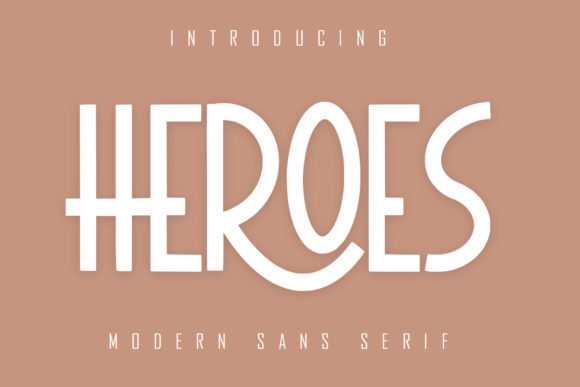
Heroes Font
Heroes Font adalah sebuah jenis huruf modern yang dirancang khusus untuk proyek-proyek bertema kepahlawanan, petualangan, dan keberanian—mulai dari poster film superhero hingga identitas merek game aksi. Dengan siluet tebal, kontras tinggi, dan sentuhan dekoratif yang terinspirasi oleh tipografi komik klasik serta desain logam tempa, font ini berhasil menyampaikan kekuatan dan keteguhan tanpa mengorbankan keterbacaan. Ketersediaan dalam berbagai weight (dari Light hingga Black) serta dukungan penuh terhadap karakter Latin, Cyrillic, dan simbol khusus membuatnya sangat serbaguna di ranah desain digital maupun cetak.
Membangun Kualitas & Detail Teknis
Dibangun dengan teknologi OpenType modern, Heroes Font menawarkan fitur-fitur profesional seperti ligatures, alternates, small caps, dan number styles (old-style & lining). Font ini tersedia dalam format .OTF dan .TTF, kompatibel penuh dengan Adobe Creative Suite, Figma, dan aplikasi desain lainnya. Setiap glyph telah dioptimalkan secara manual untuk konsistensi bentuk dan jarak antar-karakter (tracking dan kerning), sehingga tampilan teks tetap solid baik pada ukuran besar (judul) maupun sedang (subjudul). Resolusi rendering-nya luar biasa halus bahkan pada layar berdensitas tinggi (Retina/4K).
Untuk Siapa Produk Ini Terbaik?
Font ini ideal bagi desainer grafis profesional, pembuat konten media sosial bertema pop-culture, tim pengembang game indie yang membutuhkan identitas visual kuat, serta agensi kreatif yang sering menangani kampanye branding untuk produk atau acara bernuansa heroik—seperti film, serial TV, merchandise, atau even esports. Bukan pilihan utama untuk dokumen formal atau UI aplikasi berbasis teks intensif, karena sifat dekoratifnya yang dominan memprioritaskan ekspresi visual daripada fungsionalitas netral.
Gunakan Heroes Font hanya untuk teks pendek (judul, logo, tagline) dan kombinasikan dengan font sans-serif netral seperti Inter atau Manrope untuk tubuh teks—ini menjaga hierarki visual dan meningkatkan keterbacaan keseluruhan desain.
Bagaimana Dibandingkan dengan Kompetisi
Dibandingkan dengan Bangers (Google Fonts), Heroes Font menawarkan kontrol desain yang jauh lebih presisi, dukungan multibahasa yang lebih luas, dan fitur OpenType yang lebih kaya—namun tidak gratis. Jika dibandingkan dengan League Spartan, Heroes memiliki karakter yang lebih dramatis dan kurang modular, sehingga lebih cocok untuk narasi emosional ketimbang tampilan teknis. Sementara Comic Neue berfokus pada keterbacaan komik modern, Heroes Font justru mengeksplorasi estetika 'monumental'—lebih mirip patung batu daripada balon percakapan.